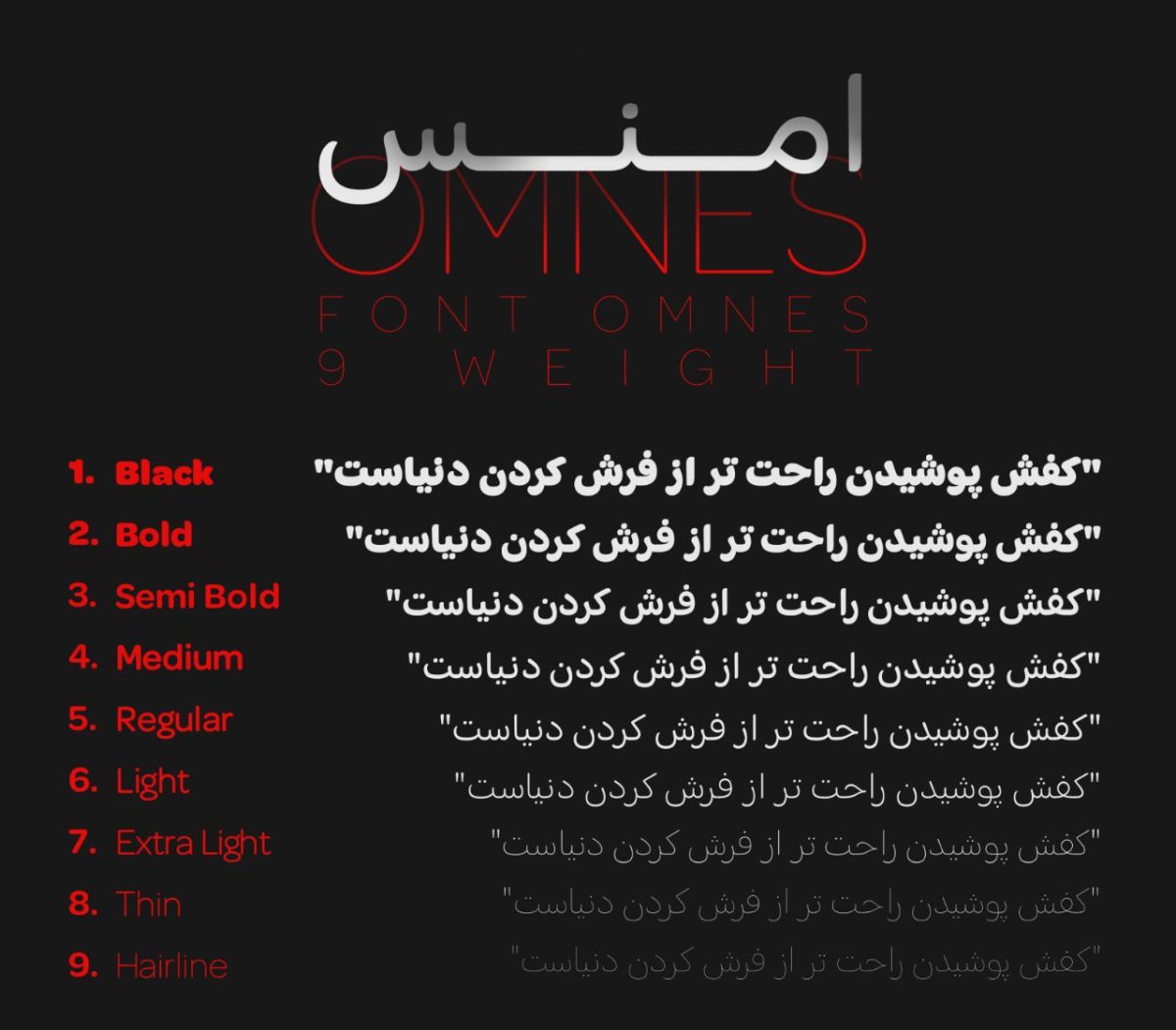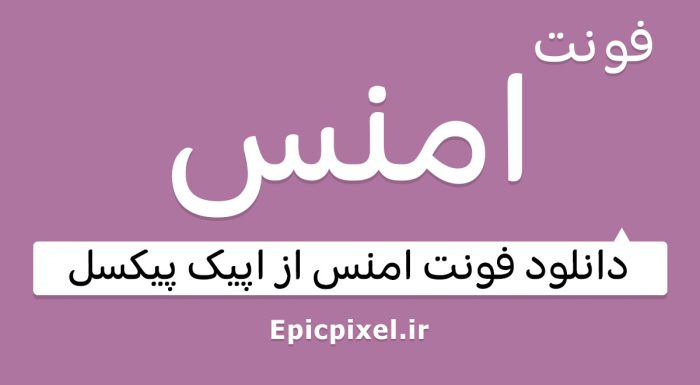
9 فونت امنس فارسی Omnes
فونت امنس (Omnes Arabic) یک قلم چندزبانه کاربردی است که برای پشتیبانی از زبان های فارسی و عربی طراحی شده است. ویژگی برجسته این فونت، ارائه آن در ۹ وزن مختلف است که تنوع وزنی کاملی را برای طراحان فراهم می آورد. فونت امنس عربیک با فرمت استاندارد و پرکاربرد TTF و به صورت کاملاً رایگان در دسترس کاربران قرار گرفته است. این مجموعه شامل وزن های Hairline تا Black بوده و آن را برای استفاده در انواع کاربردهای طراحی، از متون ریز تا عناوین اصلی، بسیار مناسب می سازد.
شناخت فونت هایی با تنوع وزنی بالا برای ایجاد سلسله مراتب بصری مؤثر در طراحی و همچنین انعطاف پذیری در کاربردهای گوناگون اهمیت دارد. فونت امنس (Omnes Arabic) یکی از این قلم ها است که به طور اختصاصی برای طراحان فعال در حوزه زبان های فارسی و عربی توسعه یافته و کارایی بالایی دارد.
ویژگی اصلی و نقطه قوت این فونت، ارائه آن در ۹ وزن مختلف است. این گستره وزنی کامل شامل حالات Hairline, Extra-Light, Thin, Light, Regular, Medium, Semi Bold, Bold و Black می باشد. این تنوع بی نظیر به طراح امکان می دهد تا متناسب با نیاز هر پروژه، از نازک ترین حالت برای متن های طولانی یا جلوه های خاص، تا ضخیم ترین حالت برای عناوین اصلی، لوگوها و تیترهای چشم نواز، فونت امنس را به کار گیرد و کنترل کاملی بر ظاهر متن داشته باشد.